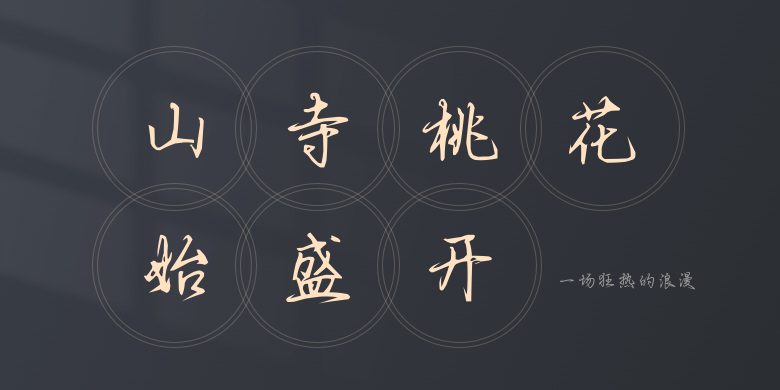
一场狂热的浪漫
一场狂热的浪漫,这款字体结构工整、笔画清晰,兼顾美观与易读性,适用于标题、正文、海报、包装、LOGO 等多种场景。字形优雅稳定,风格百搭耐看,适配日常排版与创意设计,让文字呈现更舒适、更具质感。一场狂热的浪漫一笔一画,皆是细节,以均衡的比例、流畅的线条打造舒适视觉体验,字形端正大气,风格简约现代。无论是商业设计、品牌宣传还是日常排版,都能轻松驾驭,让文字更有格调与力量。一场狂热的浪漫字体下载。